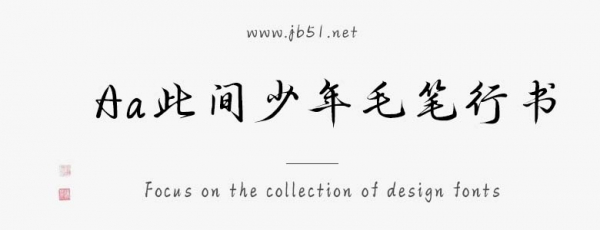
Aa此間少年毛筆行書(shū)字體筆觸l略細(xì),字形端正,書(shū)寫(xiě)流暢,具有很好的視覺(jué)感,適合應(yīng)用于藝術(shù)設(shè)計(jì)、平面宣傳設(shè)計(jì)、網(wǎng)頁(yè)設(shè)計(jì),書(shū)法字帖等領(lǐng)域。有需要的朋友快來(lái)本站下載使用吧。